小时候总是觉得老师在黑板上的板书工整优美且浑厚有力,擦黑板的时候都不忍擦掉。赏心悦目的字体彻底折服了许多学生。现在黑板字也被广泛应用在设计领域,在招牌、海报、广告等设计中都可以看到黑板字的身影。今天小编要给大家推荐几款适用于设计的黑板字,一起往下看看下面图片字体吧!
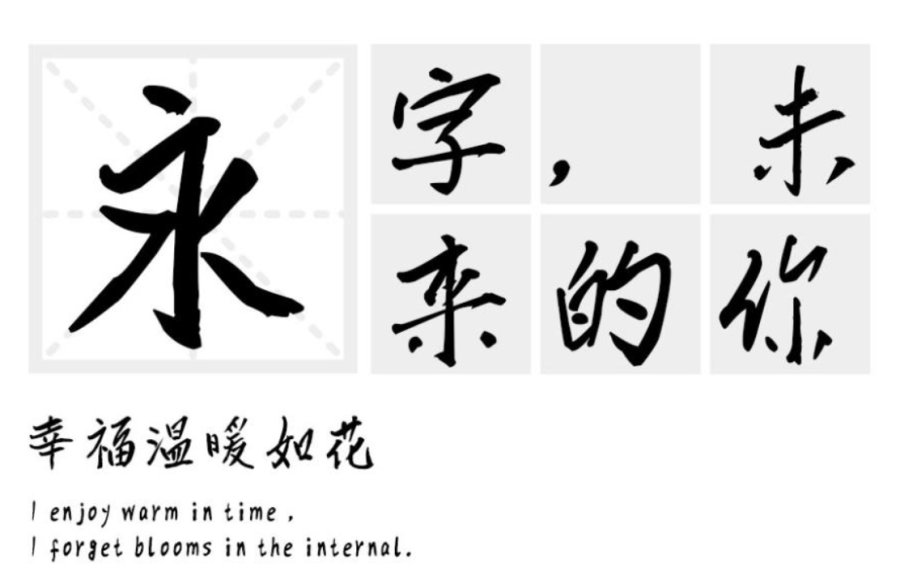
这款“汉标儒雅楷书”遵循中国传统技法,融百家之长,独树一帜,自成一体,字体个性鲜明,自然美观,典雅大方,结构严谨,比例合理,整体上给人一种舒展自如、赏心悦目的直观感受。
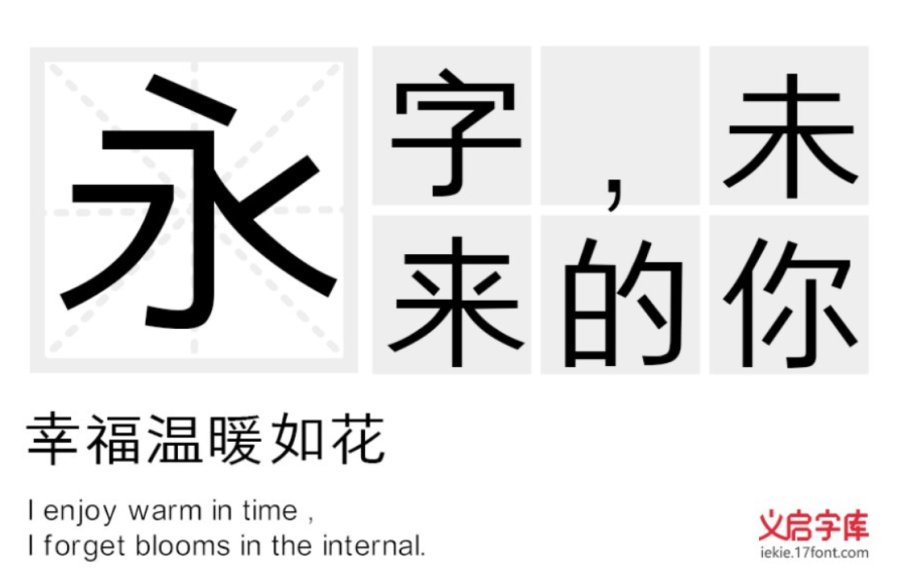
这款“义启简黑体”简约而不简单, 笔画上处理精致得当线条收笔处多以喇叭状收尾,结构经典内敛外扩重心微向上移,章法明朗流畅。结构上整体方正,字与字间的距离分配阅读舒适爽朗。尤其在手机等移动小屏幕上显示更是简约极致的体现线条美。
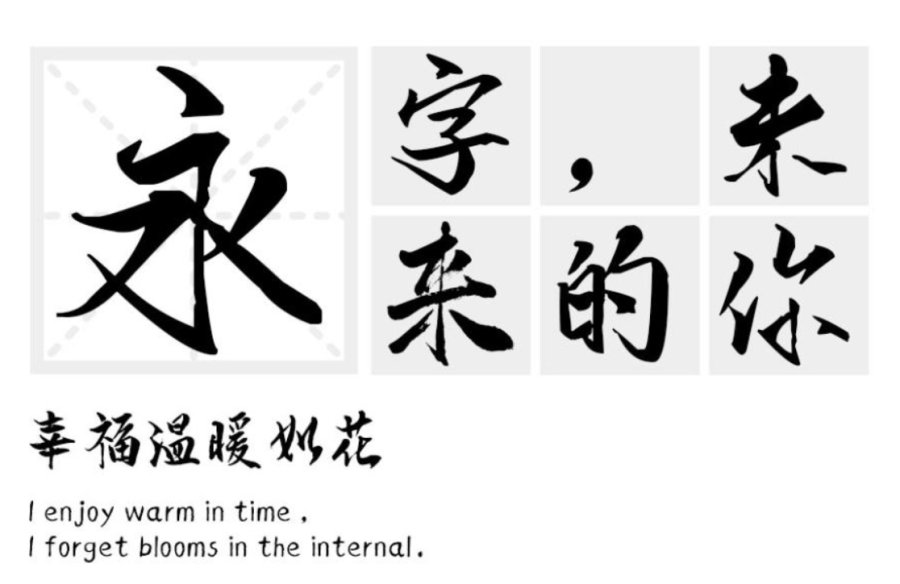
这款“汉标老梁行楷”书法气息浓厚,结字潇洒俊逸,运笔行云流水,气韵生动,充分体现新毛笔行书味道。适用于文艺类的书刊、品牌广告和产品包装设计,以及社交网络的个性化用字。